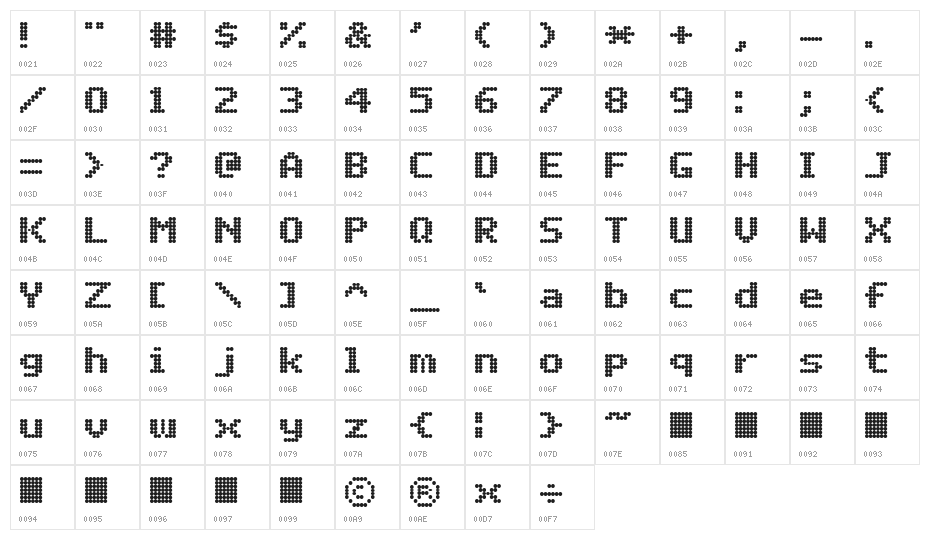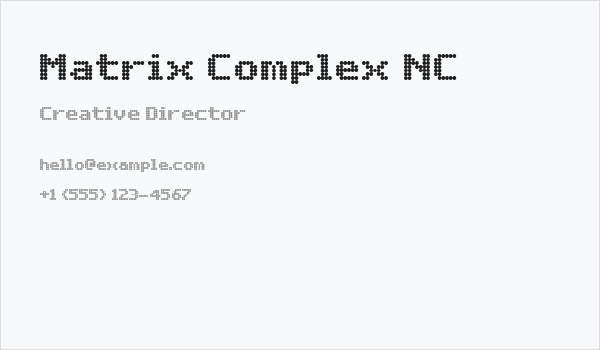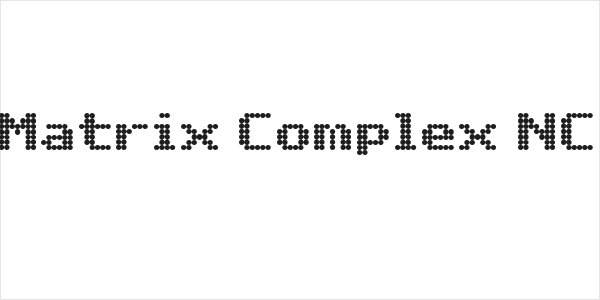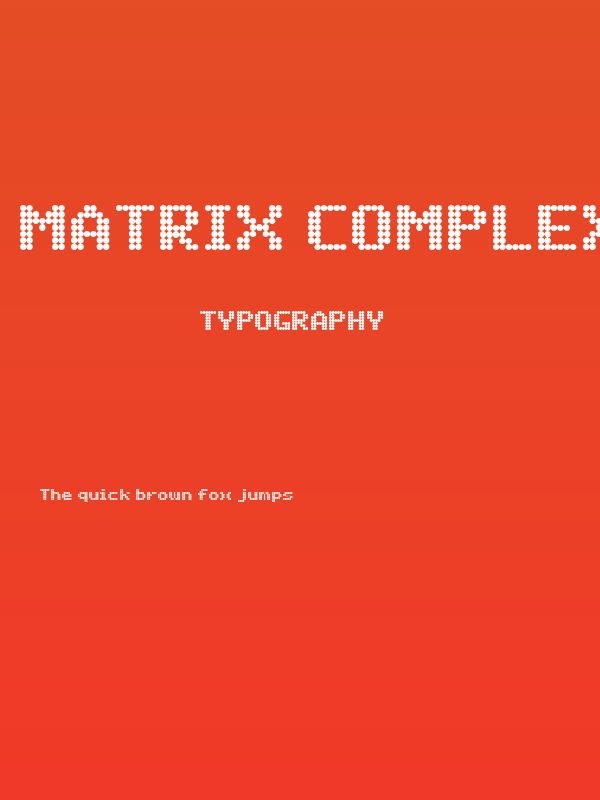
Matrix Complex NC Font
| Anwendungsfall | Logos, Headlines, Digital displays |
| Vorgeschlagene Projekte | Ideal for digital art, tech-themed designs, futuristic branding, and electronic displays. |